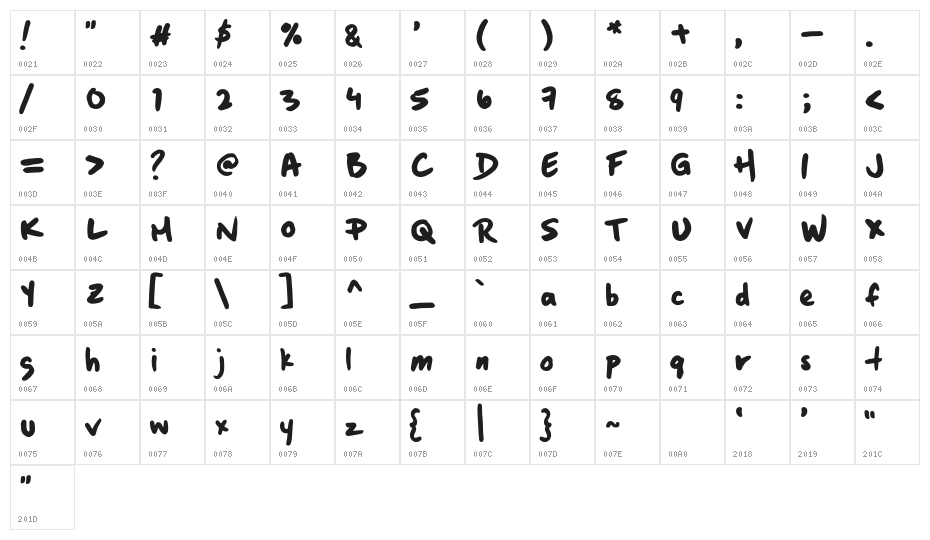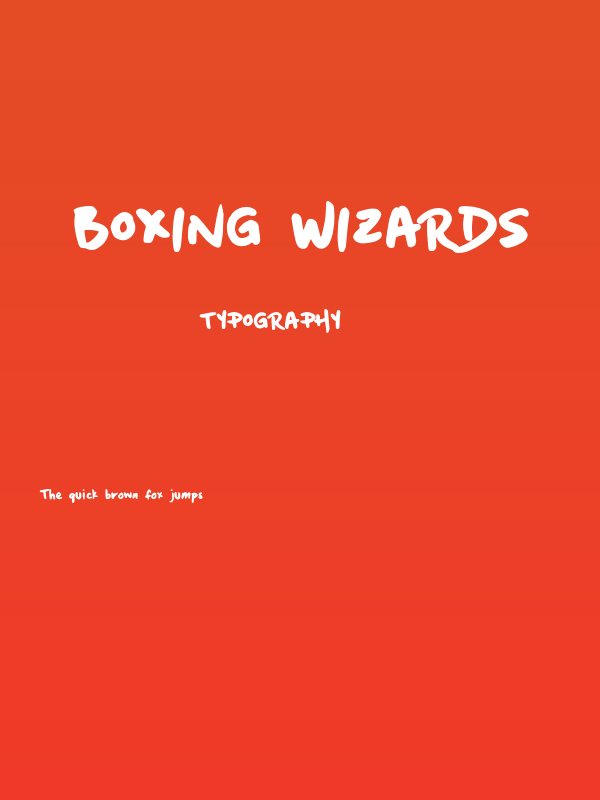
Boxing Wizards Font
| Estilo general | Playful |
| Caso de uso | Headlines, Logos, Informal Text |
| Proyectos propuestos | Ideal for children's books, playful branding, casual invitations, and social media graphics. |